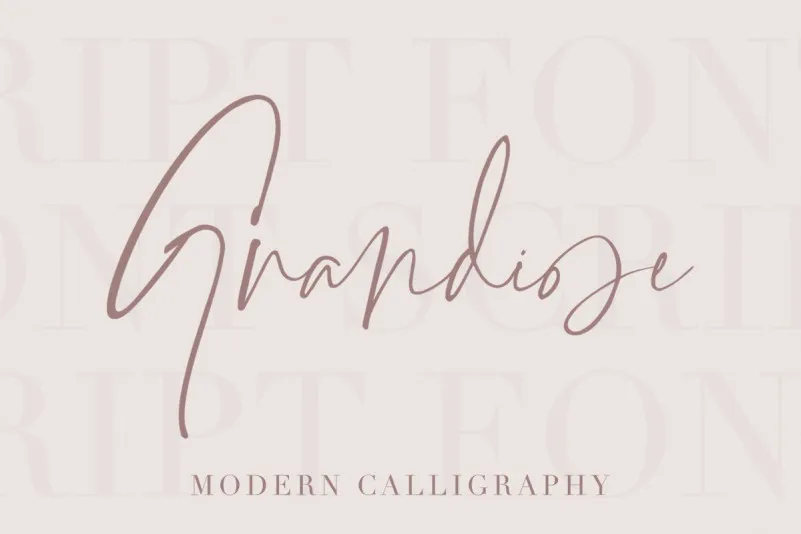
Grandiose Signature Font – Download Grátis
Bem-vindo ao mundo do design onde cada letra é uma história, e a Grandiose Signature Font é a caneta que a escreve. Esta fonte script oferece a sensação única de algo realmente escrita à mão, criada com todo o cuidado. Perfeita para aqueles que buscam um toque refinado em seus projetos, ela garantirá resultados excepcionais e resultados incríveis. Com Grandiose Signature Font, você não precisa se preocupar com a escolha certa — essa fonte combina formas elegantes de letras com uma pitada contemporânea. Ideal para criar identidades de luxo, desde marcas sofisticadas até cartões de convite apaixonados e anúncios nas redes sociais. Grandiose Signature Font também é perfeita para embalagens de produtos e cabeçalhos em mídias digitais — permitindo que você expressa seu estilo pessoalmente. Seja qual for o projeto, essa fonte irá garantir resultados impecáveis e um toque de elegância inegável. Que tal adicionar um pouco de personalidade a suas próximas criações?